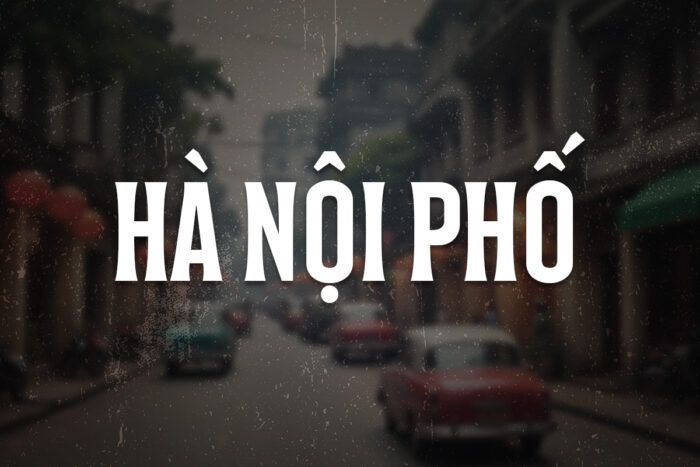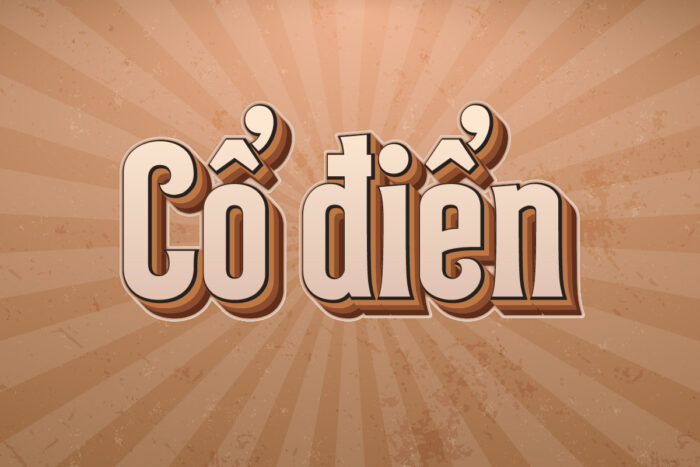
HaNoiPho – Font chữ thuần Việt kiểu củ, cổ xưa
Tạo ra một bầu không khí hồi ức cho thiết kế của bạn với Font chữ HaNoiPho. HaNoiPho là một font chữ độc đáo, mang đậm nét văn hóa và lịch sử của Việt Nam. Được thiết kế với phong cách cổ xưa, HaNoiPho tái hiện vẻ đẹp mộc mạc và tinh tế của những bảng hiệu, biển quảng cáo xưa tại Hà Nội. Với các đường nét mềm mại, uyển chuyển, font chữ này gợi nhớ về những ngày tháng khi Hà Nội còn in dấu ấn của thời kỳ bao cấp, khi các biển hiệu được viết tay bằng những nét chữ đặc trưng.